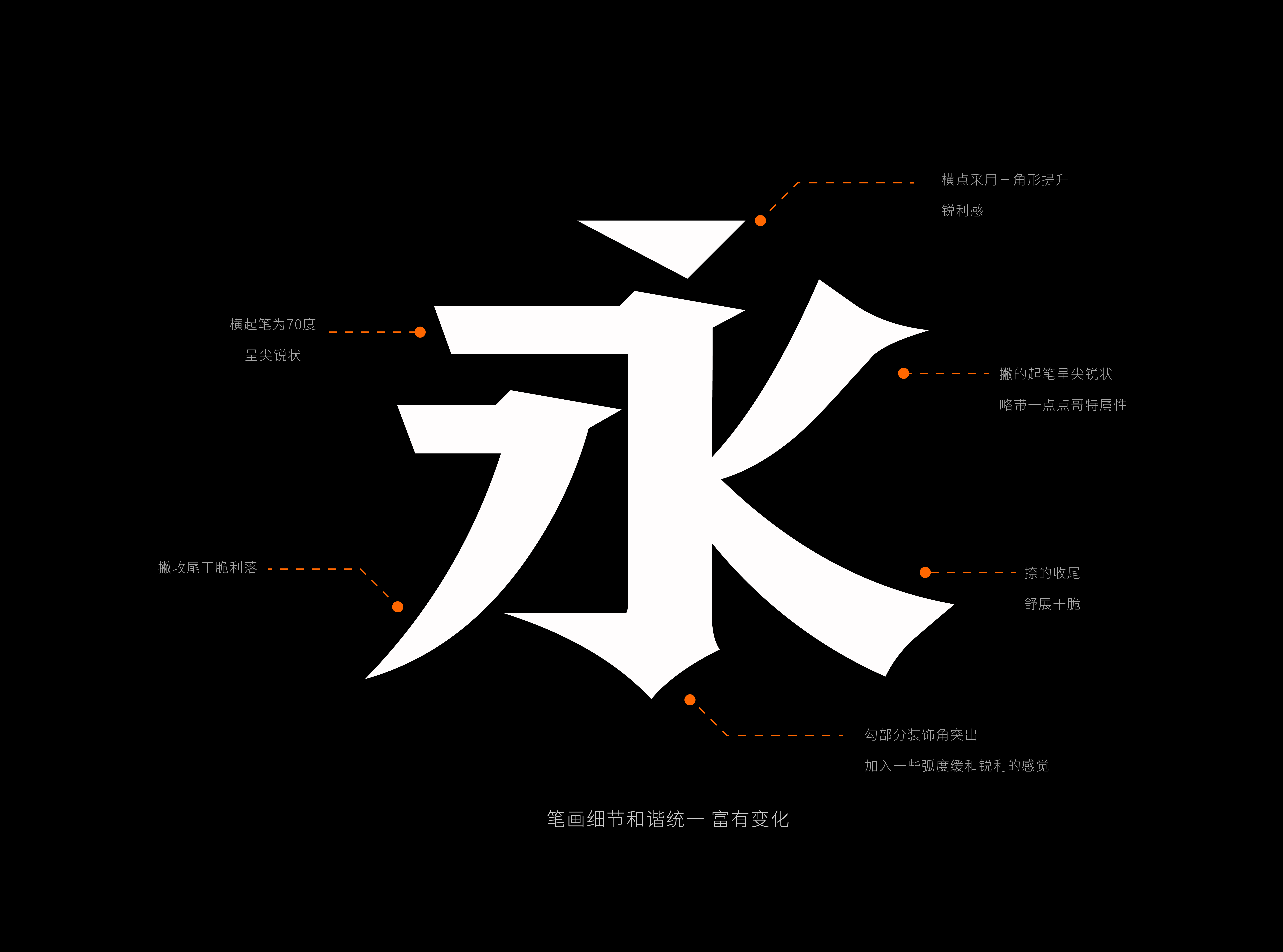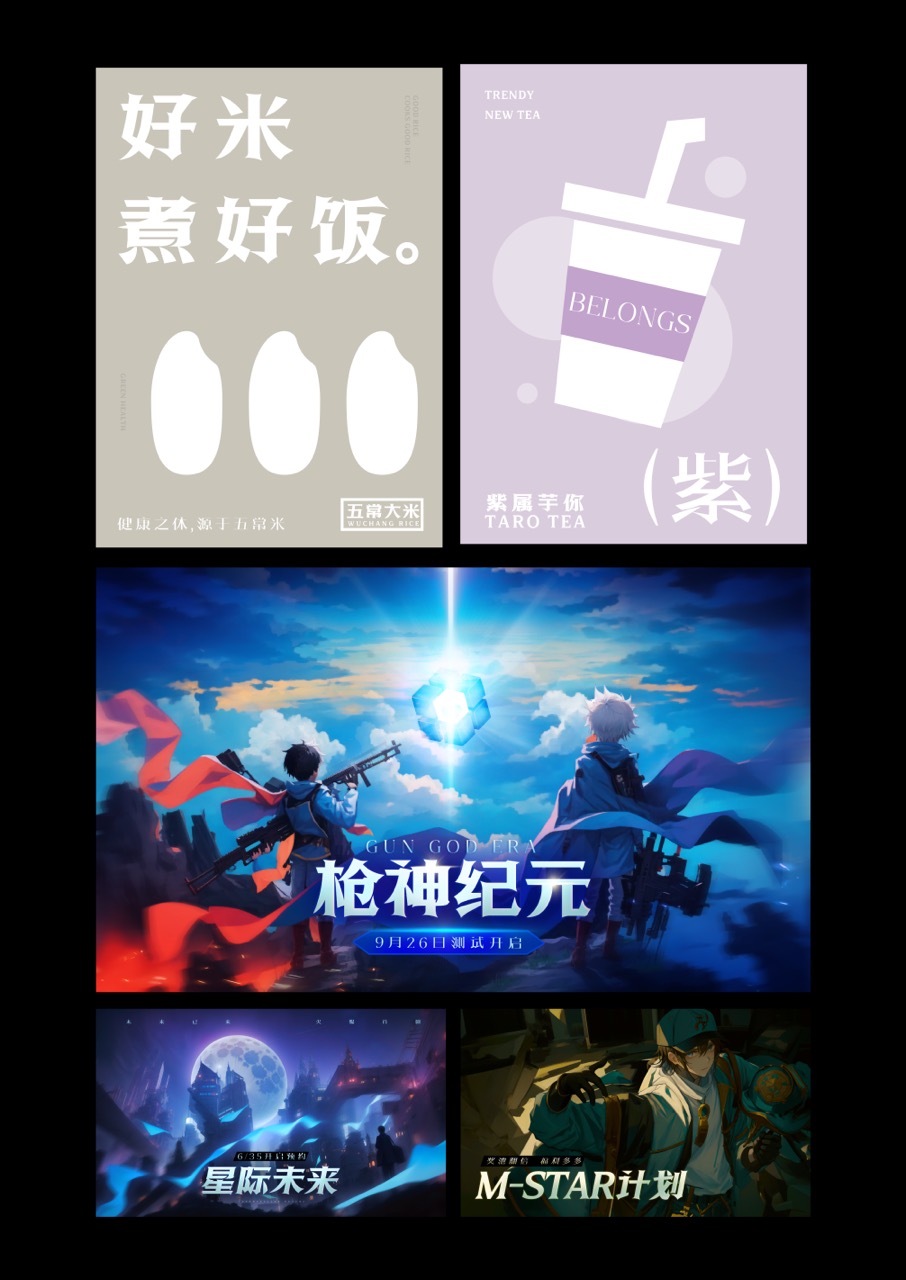
方正冷锐宋家族
字体品牌: 方正字库 设计师:冷水萧 字体分类:创意字体 字体属性:精品字 字符集:大陆简体(GB2312-80) 发布时间: 2024
这是一款特异的宋体变体字,主要笔画特征类似宋体,中宫偏大,字体呈扁状长方形,笔画细节锐利,具有冲击力,本款字适用于品牌标志、招牌、广告、包装、游戏、设计等众多场景。